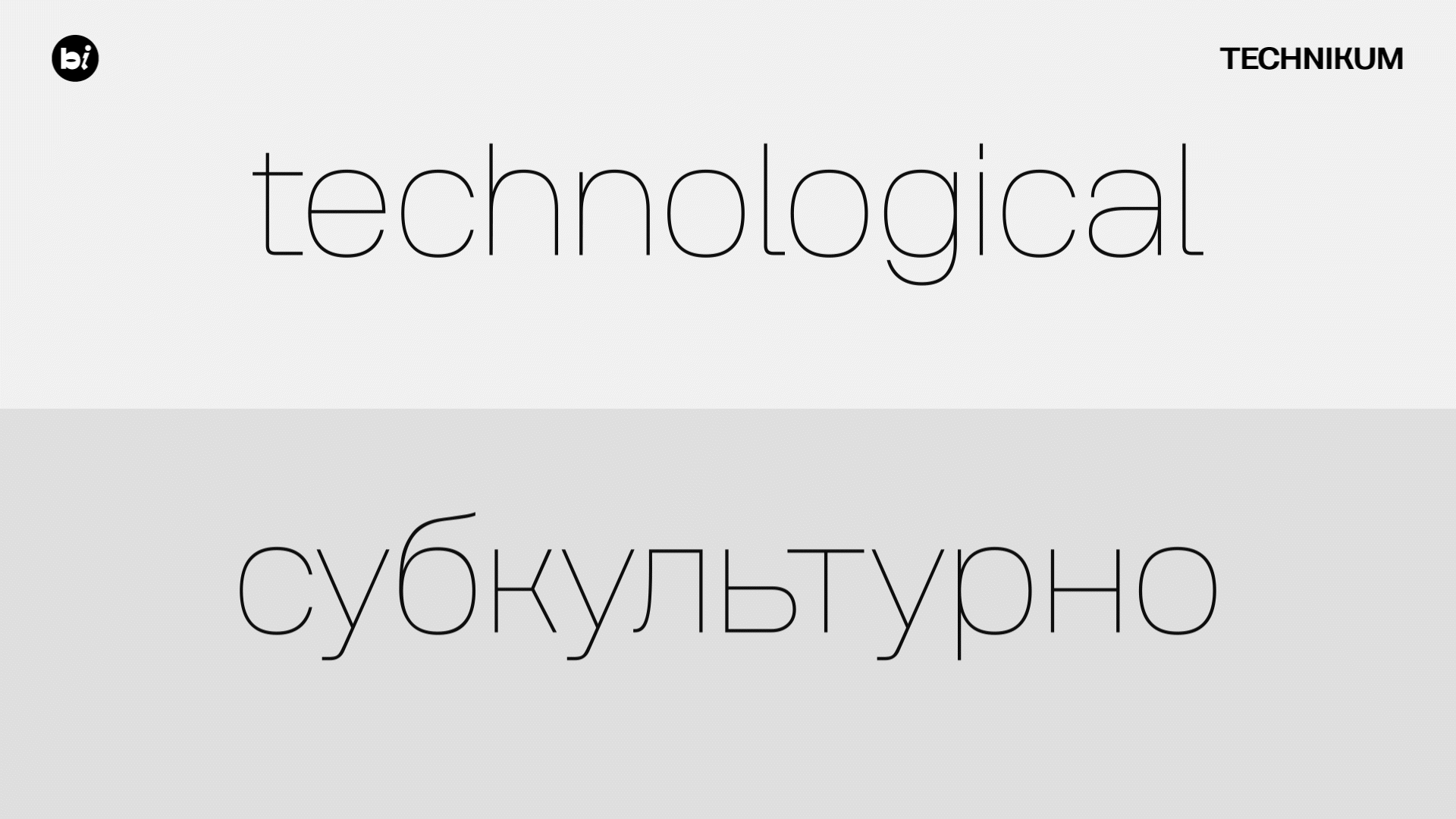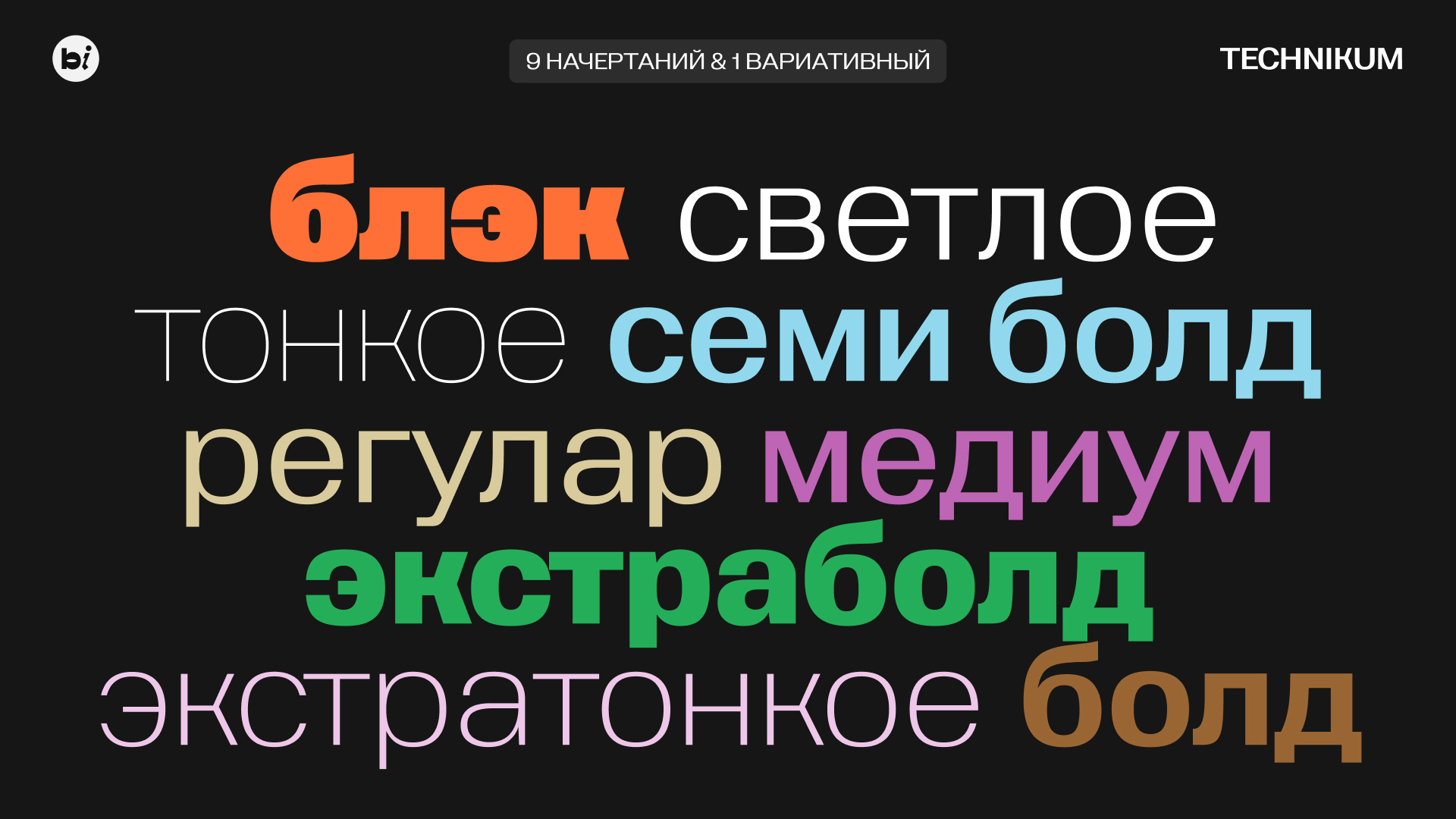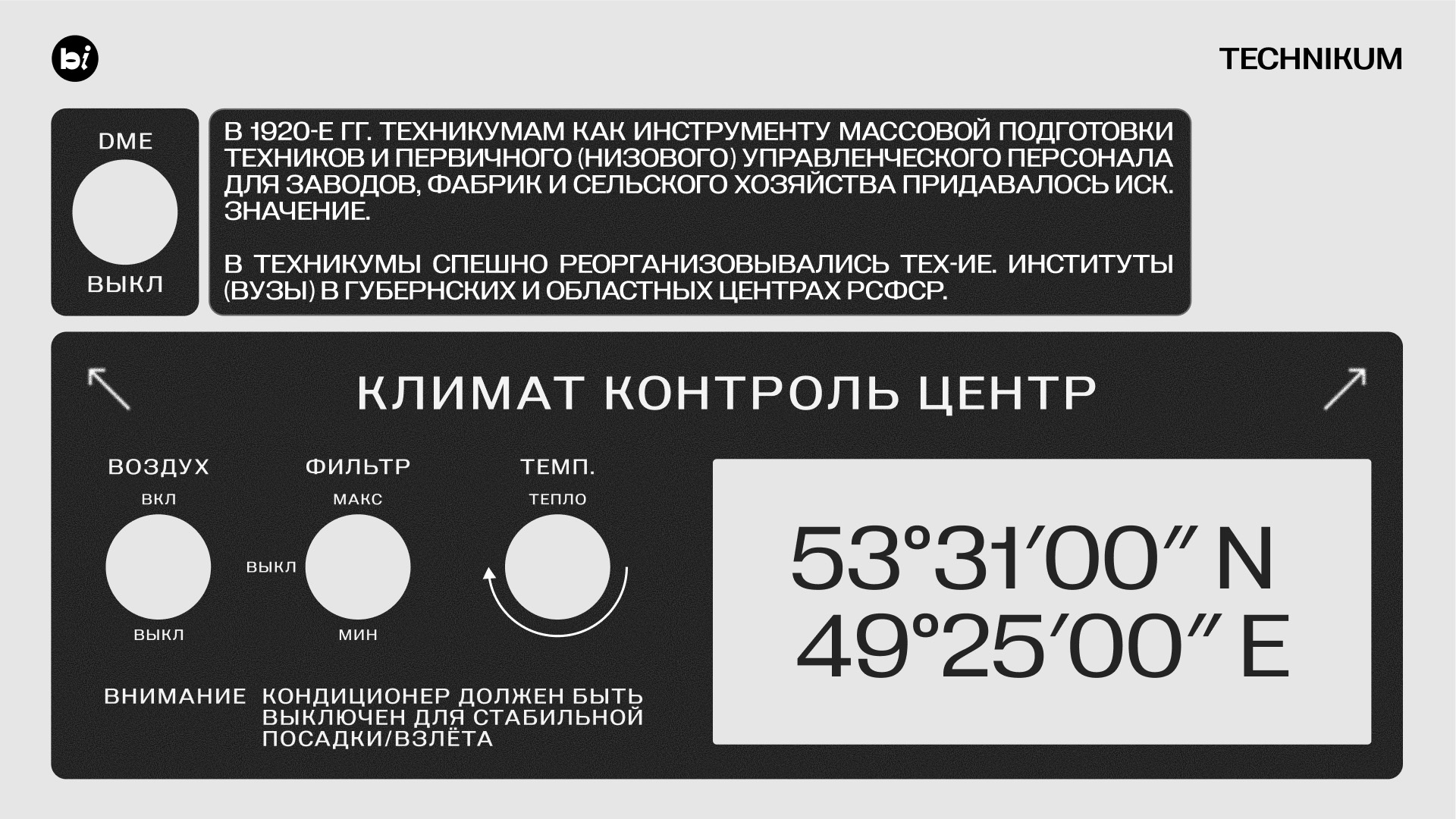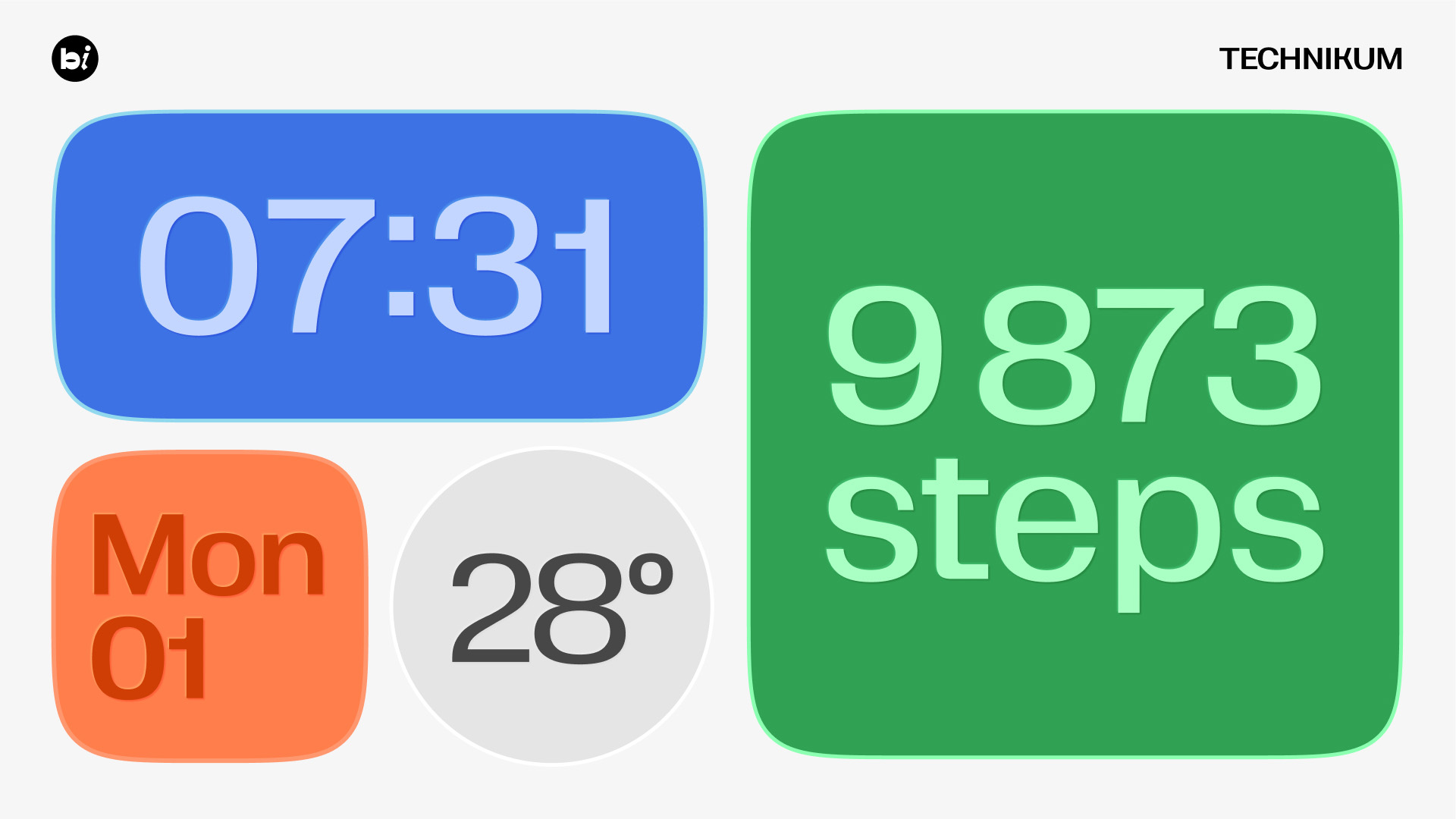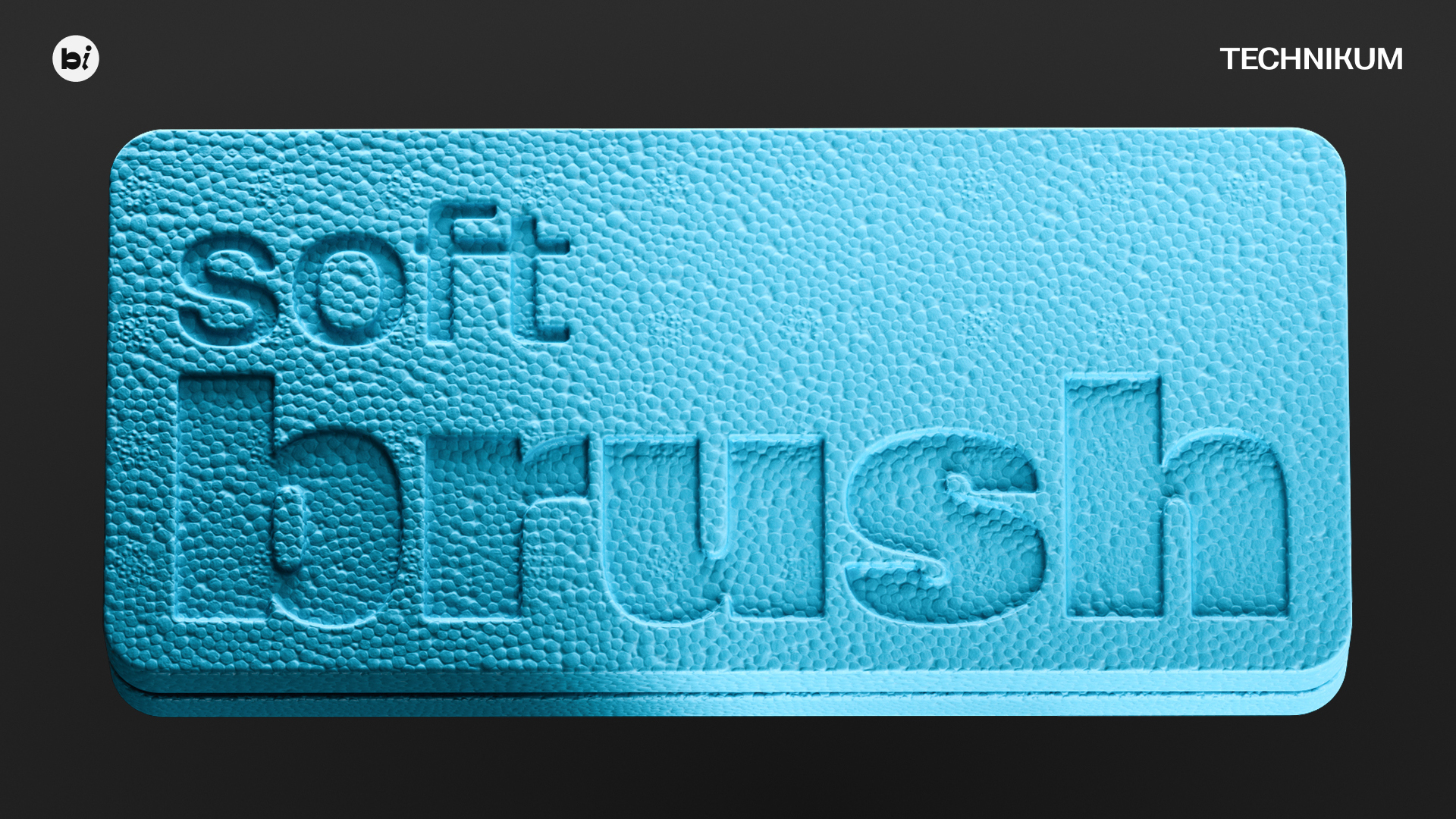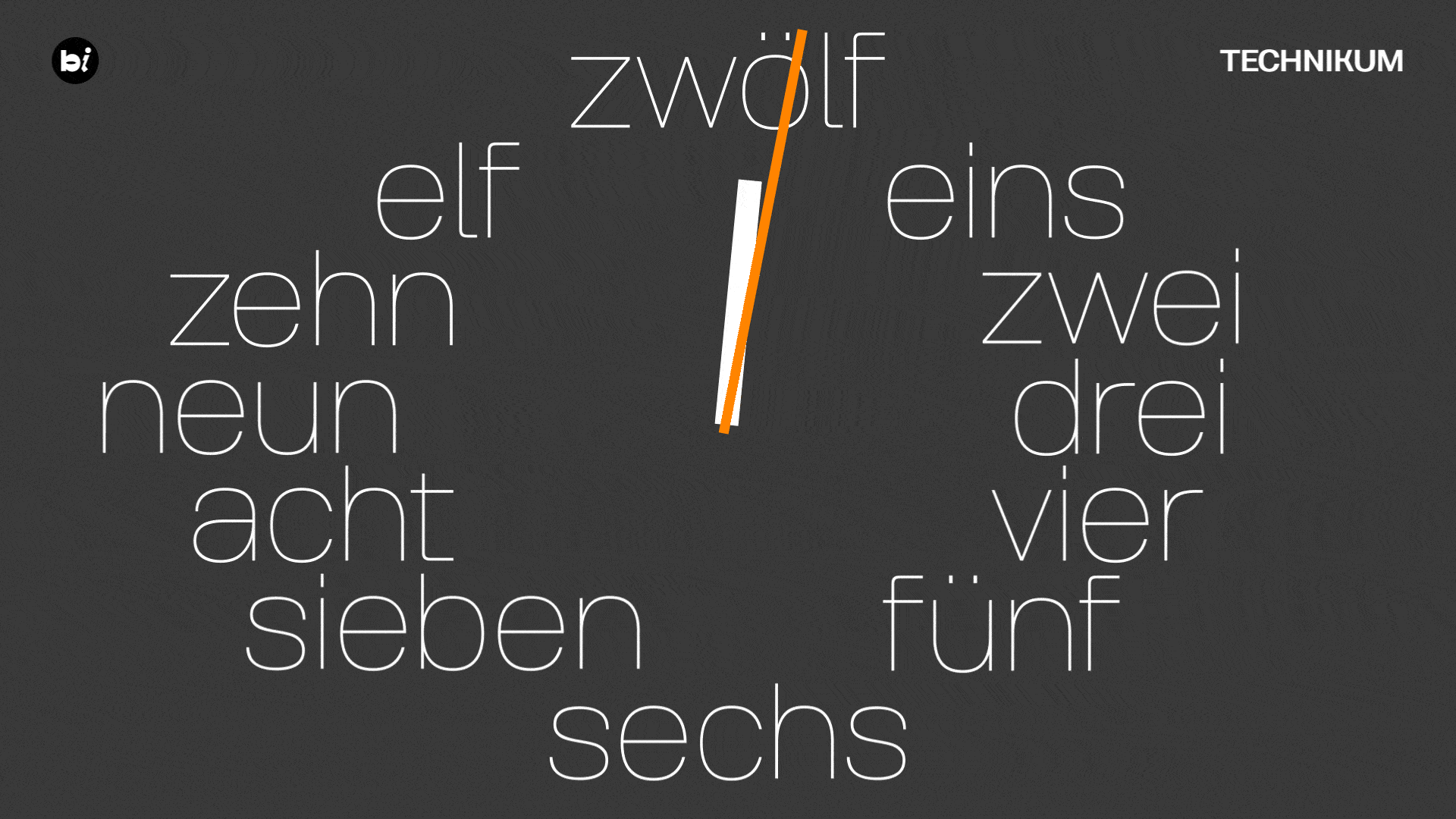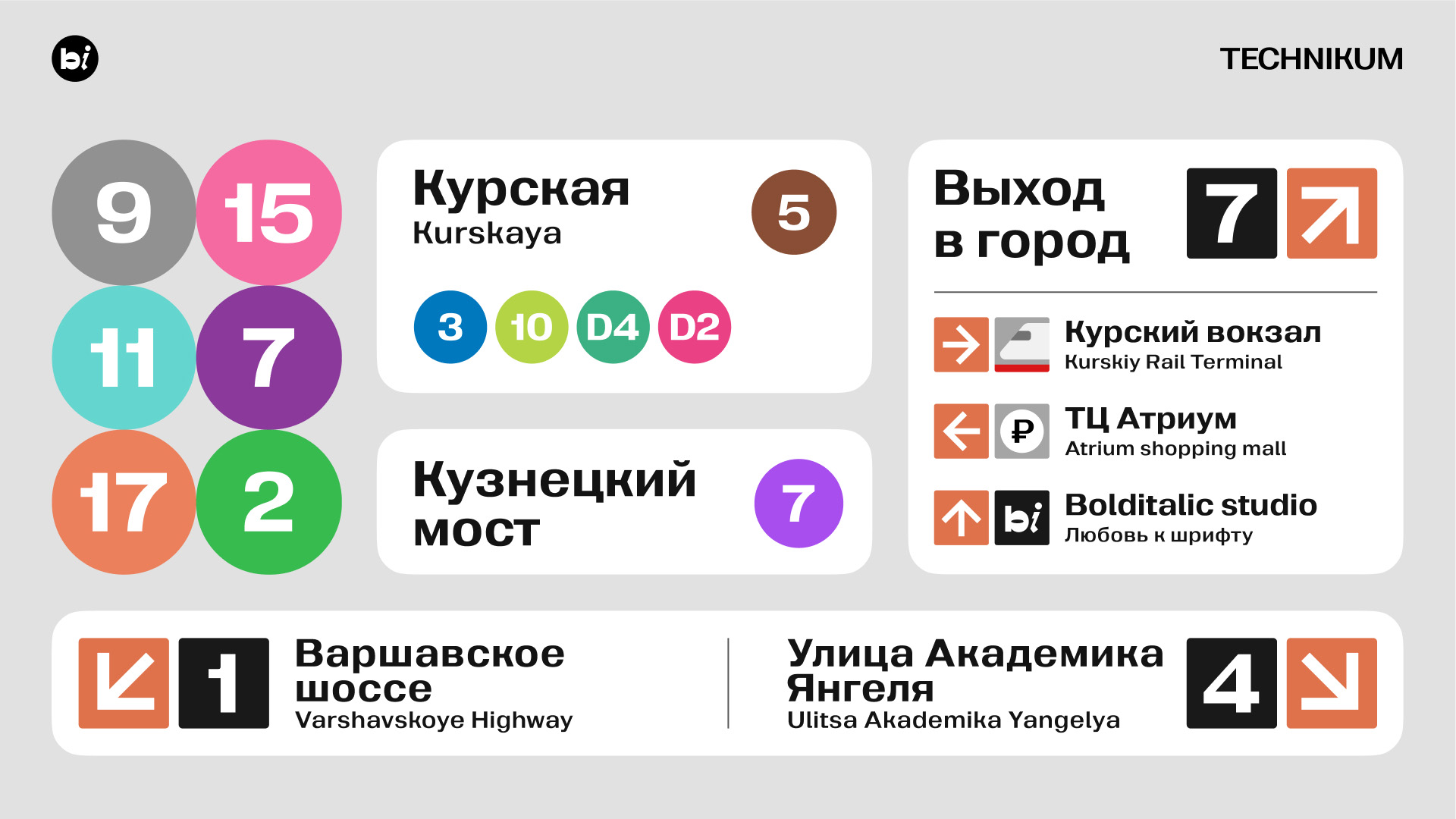
Technikum
Вариативный закрытый гротеск с брутальными очертаниями и приквадраченными овалами. В начертании Regular у него полузакрытые апертуры, а в Black они становятся почти герметичными. Контраст конструкций формирует баланс между технологичной точностью и дружелюбным характером.
Студия Болдиталик
Макс Кудашов, Шрифтовой дизайн, арт-дирекшн промо
Дмитрий Голуб, Арт-дирекшн шрифта
Евдоким Антонов, 3D и анимация
Расим Насибов, Музыка и эффекты